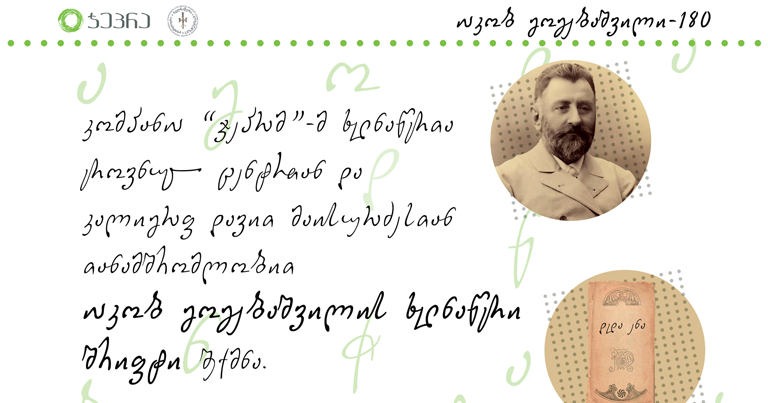
27 ოქტომბერს, იაკობ გოგებაშვილს 180 წელი შეუსრულდა!
იუბილესთან დაკავშირებით, „ჯეპრამ“ გადაწყვიტა, საჩუქარი გაეკეთებინა ქართველი მკითხველისა და ყველა დაინტერესებული ადამიანისთვის და ხელნაწერთა ეროვნულ ცენტრსა და კალიგრაფ დავით მაისურაძესთან თანამშრომლობით, იაკობ გოგებაშვილის ხელნაწერი შრიფტი შექმნა.
„ჯეპრას“ ინიციატივითა და მხარდაჭერით შექმნილი, ეს უკვე მეორე შრიფტია. პირველად, 2019 წლის გაზაფხულზე, ნიკო ნიკოლაძის ხელნაწერი გაციფრულდა.